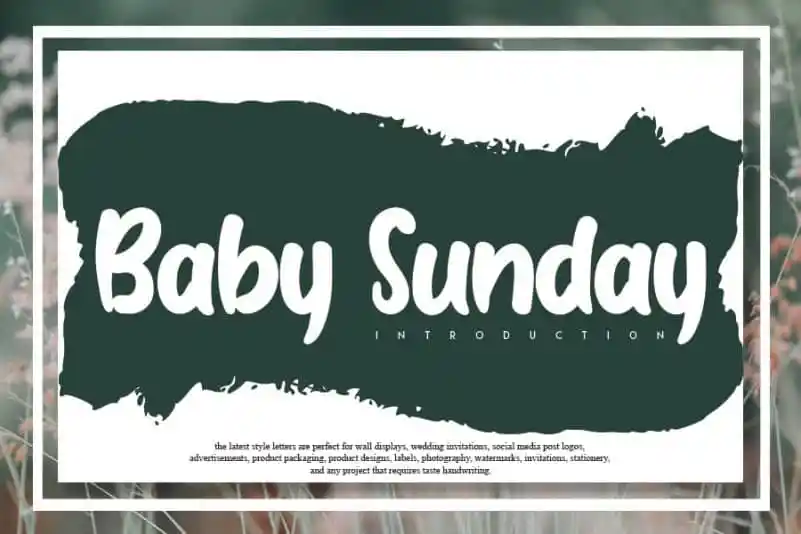
Baby Sunday Display Font – Download Grátis
A Baby Sunday Display Font é uma criação única que resulta de uma harmoniosa combinação de um pincel e uma pena espartilho, produzindo um resultado encantadormente autêntico. Esta elegante fonte escrita à mão ganha vida em projetos DIY de forma incrivelmente encantadora, tornando-a perfeita para adicionar um toque especial às suas criações. Seja ela uma etiqueta, um recado personalizado ou até mesmo a capa de um álbum de fotos, Baby Sunday Display Font trará sua personalidade e originalidade ao design. Ideal tanto para aqueles que valorizam o handmade quanto para designers em busca de algo surpreendente e autêntico, esta fonte escrita à mão irá deixar seu trabalho ainda mais encantador.